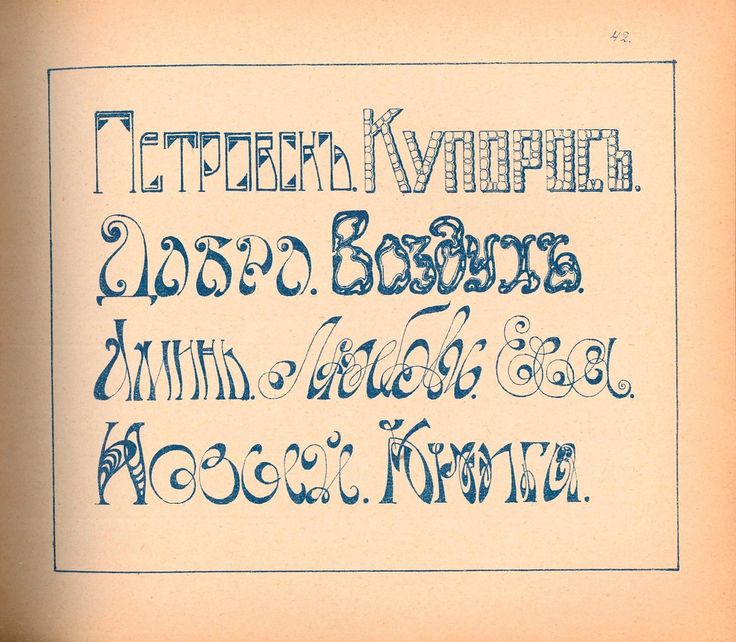
Мы сделали фирменный шрифт для Додо Пиццы! Это открытый гротеск со скругленными окончаниями — функциональный, вариативный, и очень дружелюбный.
Читатели прекрасно помнят серию книг «Великие шрифты».
Из задуманных пяти томов вышло только два, а вся серия была посвящена наборным шрифтам, оказавшим серьёзное влияние на типографическую среду. Планировался третий том, посвящённый гротескам, часть статей была написана, но осталась неопубликованной. Мы подготовили очерк Анны Шмелёвой и Владимира Ефимова о знаменитом гротеске Эрика Гилла — о том, как он был задуман и выпущен, как его использовали в XX веке и используют сегодня.
Шрифт — это не только дизайн. Современный шрифт — это сложный цифровой продукт, который объединяет данные разных типов. Это и математика описания кривых, и программный код, и инструкции по настройке отображения знаков на экране.
Вторая часть истории шрифта на экране — от цветных мониторов конца 90-х до того, как они работают сейчас. Если вы не знаете, что такое хинтинг, то лучше сначала прочитать первую часть — без неё может быть не очень понятно : )
Сейчас все уже привыкли к тому, что в печати и на экране используются одни и те же шрифты, выглядят они примерно одинаково, а иногда у экранных шрифтов даже больше возможностей.
Но так было не всегда.
Стас Поляков, креативный директор дизайн-компании «Смена», которая с 2016 года занимается созданием дизайн-системы для всех государственных сайтов, рассказал, как родился шрифт Golos RF и зачем он понадобился.
Арт-директор студии Paratype Александра Королькова рассказала про разновидности шрифтов и их характер.Подробнее
Если у проекта небольшой бюджет и отдельные деньги на покупку лицензии на шрифт в нём не предусмотрены, это уже давно не значит, что выбирать придётся только из Arial, Times New Roman и Roboto. Если мы говорим о проекте, активно использующем кириллицу, то выбор всё равно есть — из нескольких десятков, а то и сотен шрифтов.
Владимир Ефимов (1949–2012) создавал новые шрифтовые гарнитуры и восстанавливал уцелевшее наследие Отдела наборных шрифтов НИИ Полиграфического машиностроения, а также писал статьи, выступал на профессиональных конференциях (и принимал участие в их организации), устраивал с коллегами международные шрифтовые конкурсы, обучал студентов, переводил и редактировал книги.
Итак, вы решили создать свой шрифт — именно тот шрифт, который необходим вашей компании или клиенту. Вы подготовили эскизы, поработали над формой знаков, преобразовали изображение в кривые и, возможно, перенесли контуры в шрифтовой редактор (или с самого начала работали в шрифтовом редакторе). Что дальше?
Шрифт Futura – одно из самых ярких и типичных порождений своего времени. Вдохновленные голландским движением De Stijl, русским конструктивизмом и школой дизайна Bauhaus в Германии с ее девизом «форма определяется функцией», европейские дизайнеры на всем протяжении 1920-х годов эксплуатировали элементарные геометрические формы, такие, как квадрат, треугольник, круг.
Компьютер — всего лишь инструмент, и оператор или дизайнер, даже при самой совершенной машине, но без ясного понимания своей задачи, без профессиональных знаний, не сможет работать на требуемом уровне.
Современные средства обработки текста и иллюстраций, самые лучшие издательские пакеты в наших условиях тоже не гарантируют автоматического успеха. В статье описаны методы и правила набора и вёрстки.
Английский каллиграф, резчик по камню, издатель, изобретатель и дизайнер шрифта Джон Баскервиль родился в 1706 году в Уолверли (Wolverley) в графстве Уорчестершир и в 1725 году в возрасте 19 лет перебрался в Бирмингем, где начал работать как каллиграф и резчик по камню. В 1750 году Баскервиль открыл в Бирмингеме собственную типографию, словолитню и бумажную мельницу, и последующие 25 лет он потратил все свое состояние на издательскую деятельность.